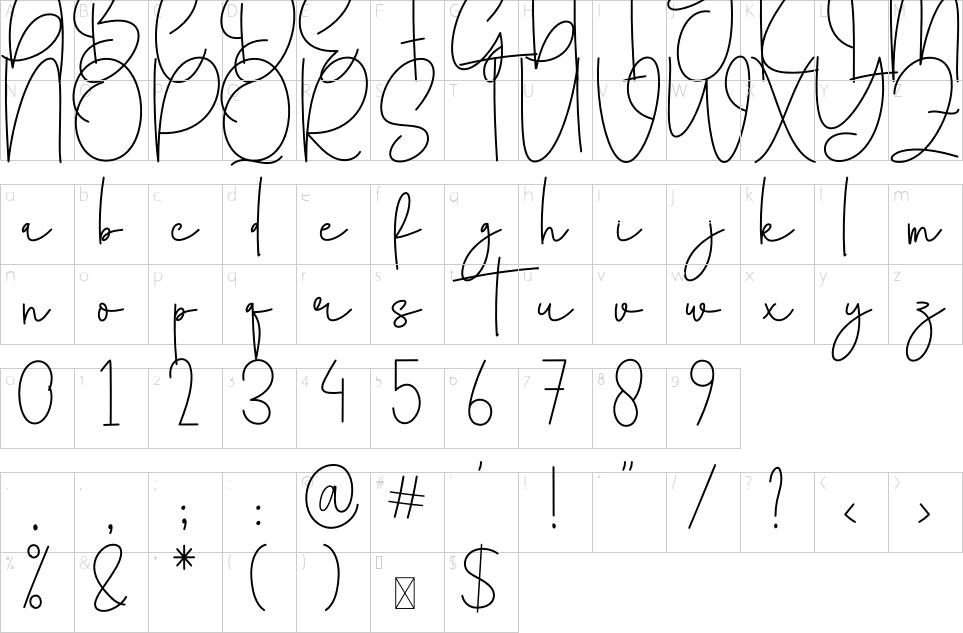
Descubra Delightful Font, uma elegante e minimalista escolha para seus projetos digitais gratuitos. Desenvolvida por William Jhordy, esta fonte vem com um design sofisticado que será ótimo para criar gráficos de alta qualidade ou simples designs profissionais. Com seu download gratuito disponível tanto no Windows quanto na versão Mac, Delightful Font pode ser uma excelente opção para designers e criativos que desejam adicionar um toque único a seus trabalhos sem precisar pagar. Além do design elegante, Delightful Font também oferece recursos práticos que garantirão que sua fonte funcione perfeitamente em qualquer dispositivo ou sistema operacional. É uma escolha inteligente para quem busca um equilíbrio entre beleza e facilidade de uso.